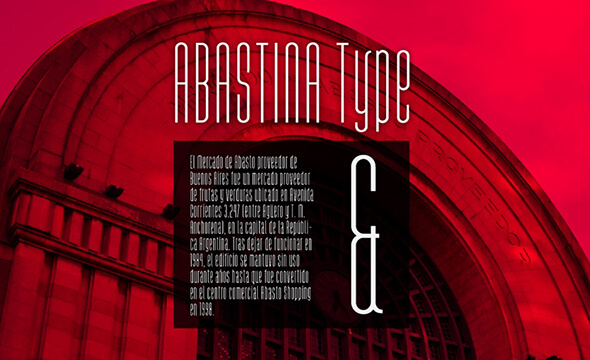
【商用可能なフリーフォント】無料でダウンロードできる固定幅フォント20選
フリーフォントはフリービーコレクションに幾つ加えても足りません!この記事では、無料でダウンロードできる20種類の固定幅フォントをご紹介しています。しかし、なぜ固定幅フォントは通常のものよりも特別なのでしょうか?このタイプのフォントは自動的に整列し、すべての文字が同じ幅となり、テキストをより読みやすくします。その規則性とバランスが、固定幅フォントを様々なオンラインプロジェクトにとって実用的なものにします。固定幅フォントは確実にどんなWebデザイナーやグラフィックデザイナーにも便利です。
オンラインと印刷物の両方のプロジェクトに固定幅フォントを使用できます。あなたが求めるもの次第で、ポスター、Tシャツ、看板、ロゴ、ウェブやゲームのグラフィックなどに利用できます。
これらを念頭に置いて、優れた固定幅フォントのコレクションをご覧頂き、今後のプロジェクトにそれらを活用して下さい。
Cherry Fixed Width Font
これは、さまざまなプロジェクトで使用できる素晴らしい固定幅の書体です。それは軽量デザインであり、コードラインを書くのに最適です。
Futurist Fixed Width Font
これもまた、開発者、Webデザイナー、またはプログラマーに便利な固定幅フォントです。
Monofur Fixed Width Font
もう一つの素晴らしい固定幅の書体がここにあります。すべての文字が同じ幅になり、読みやすくなります。
Secret Code Fixed Width Font
あなたのプロジェクトにこのすっきりとした書体をダウンロードして使用してください。このフォントは無料でダウンロードして使用できます。
Lotte Paperfang Fixed Width Font
これは、幅が固定されたもう一つの優れたフォントです。ダウンロードして今後のプロジェクトに使用してください。
Abastina Fixed Width Font
下のイメージを見て、この書体があなたのスタイルに合っているかどうか確認して下さい。現在または今後のデザインのためにそれで何が出来るかイメージしてみて下さい。
Borgen Fixed Width Font
これはシンプルな軽量タイプの書体で、個人的な目的に無料でダウンロードして使用できます。商用に利用するために必要な場合は、ライセンスファイルを確認してください。
Unispace Fixed Width Font
Unispaceは、均整のとれた固定幅の書体です。個人的なプロジェクトと商用プロジェクトの両方に使うことができます。
Normafixed Fixed Width Font
ここに、印刷のプロジェクトとデジタルのプロジェクトの両方に無料で使用できるきれいな固定幅フォントがあります。商用プロジェクトで使用する場合は、ライセンスファイルを確認してください。
NovaMono Fixed Width Font
これは、プログラマー、開発者、またはWebデザイナーにとって便利な固定幅の素晴らしい書体です。
ElroNet Monospace Fixed Width Font
さまざまな印刷物やデジタルプロジェクトで使用できるもう一つの美しい固定幅の書体がここにあります。
SmallType Writing Fixed Width Font
これは、多目的プロジェクトで可読性を向上させるために使用できる素晴らしいフォントです。この固定幅の書体は、プリントまたはデジタルデザインで完璧に表示されます。
Liberation Mono Fixed Width Font
これは対称的なデザインとバランスのとれた文字を持つ素晴らしい書体です。さまざまなプロジェクトに無料でダウンロードして使用できます。
Pointfree Fixed Width Font
この固定幅書体は、さまざまな印刷物やデジタルプロジェクトで使用できます。このフォントは、すべて同じ幅の丸みのある文字を持っています。
Verily Serif Mono Fixed Width Font
この書体をダウンロードして使用すると、完璧に表示されて読みやすい、素晴らしいプロジェクトを作成することができます。
Big Pixel Fixed Width Font
独特なデザインだけでなく、ライト、レギュラー、シャドーの3つのバリエーションのある、クリエイティブな固定幅フォントがここにあります。
Larabie Font Fixed Width Font
この書体は、丸みを帯びたエッジを持つきれいな文字デザインです。それは固定幅フォントで、無料でダウンロードして使用できます。
Aurulent Sans Mono Fixed Width Font
これは、Webデザイナー、プログラマー、または開発者にとって便利な、固定幅デザインの包括的な書体です。
ModeNine Fixed Width Font
これは様々なプロジェクトで使用できる固定幅の美しい書体です。商用プロジェクトで使用する場合は、ライセンスファイルを確認してください。
XLMonoAlt Fixed Width Font
これは無料でダウンロードして使うことができるもう一つの素晴らしい固定幅の書体です。